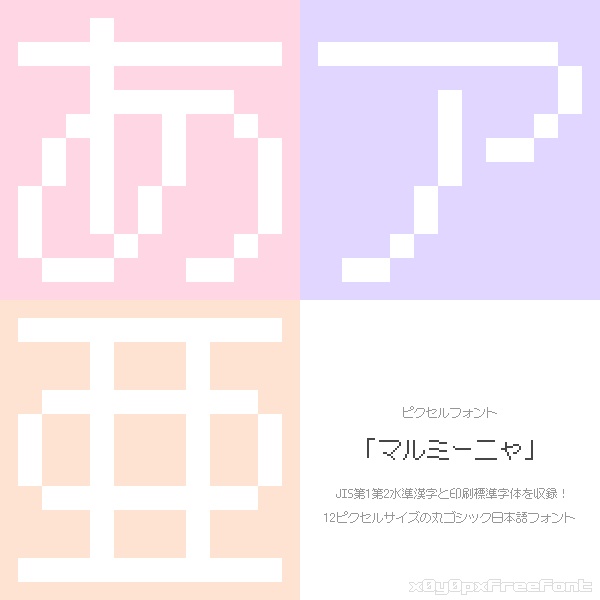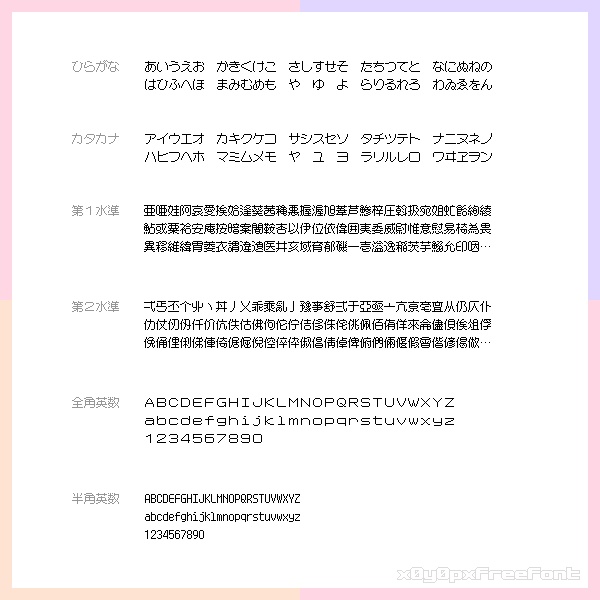
MaruMinya「マルミーニャ」是一个基于12像素大小的圆角哥特风格像素字体。它以其大字形和广泛的留白为特点,通过整齐排列的像素布局实现了良好的可读性。
这是一种在“可爱”中融入了“认真”的字体,能够适应各种用途的像素表示。
该字体收录了丰富的汉字,包括JIS第1水平汉字2965个和第2水平汉字3390个。它还支持印刷标准字体,非常适合包含广泛汉字的日语文本。 ※ 不支持竖排文字。
“x12y12px Maru Minya”是一款书写很新颖的字体,字体大方,适合各种设计作品使用!欢迎下载!